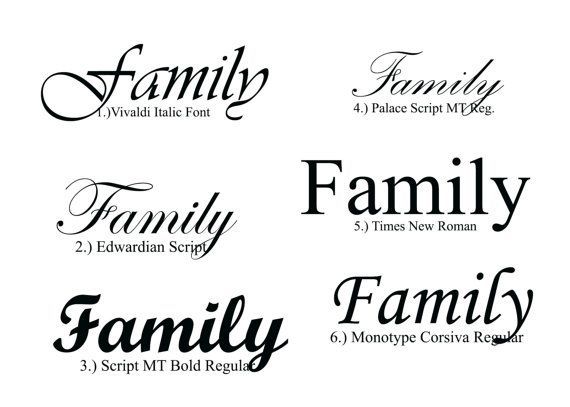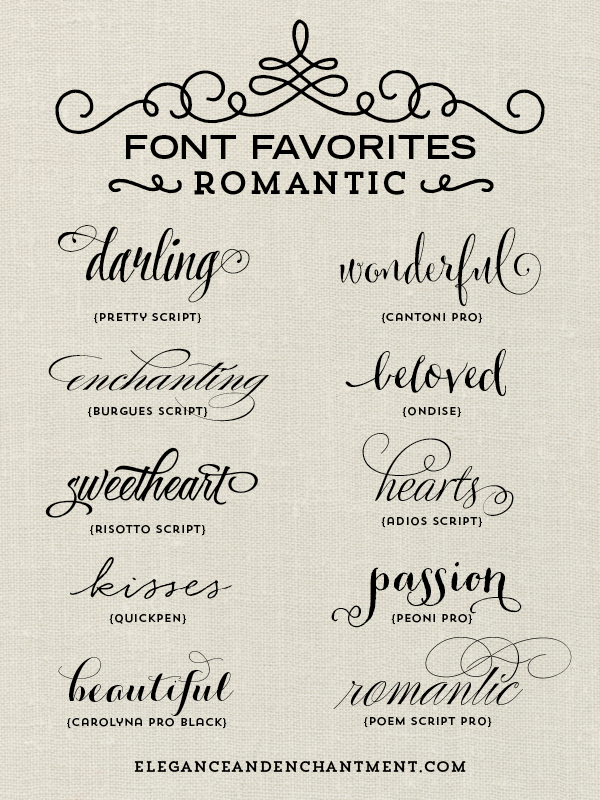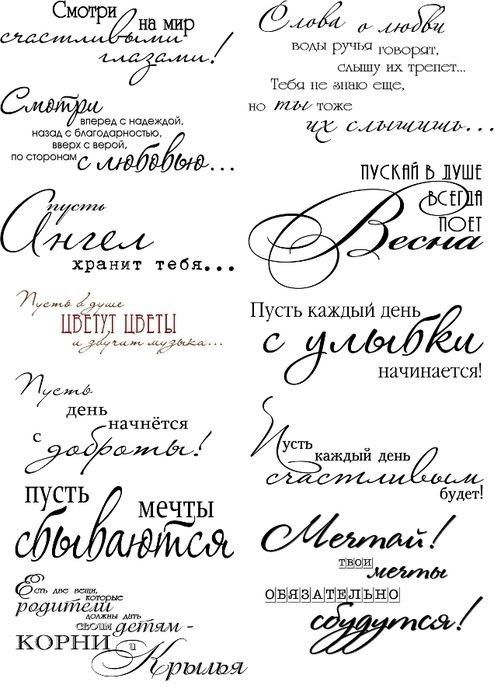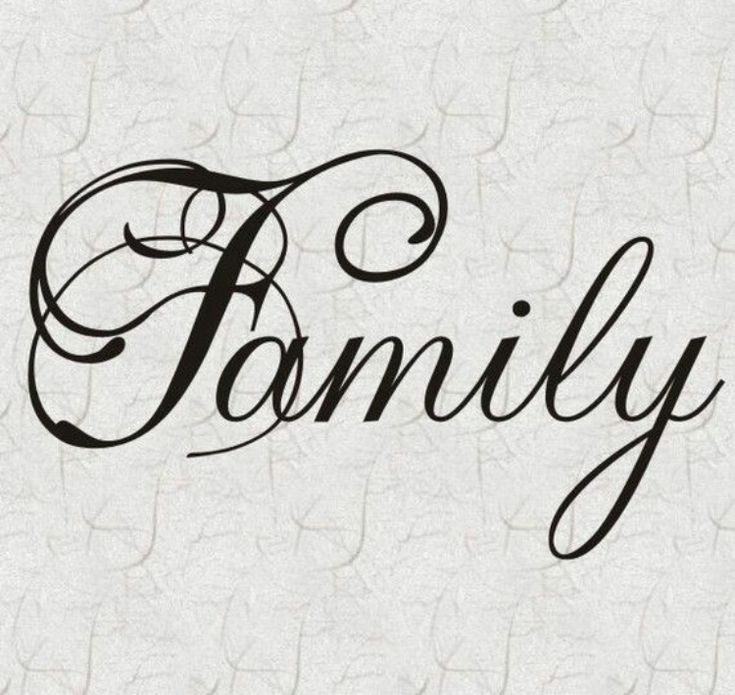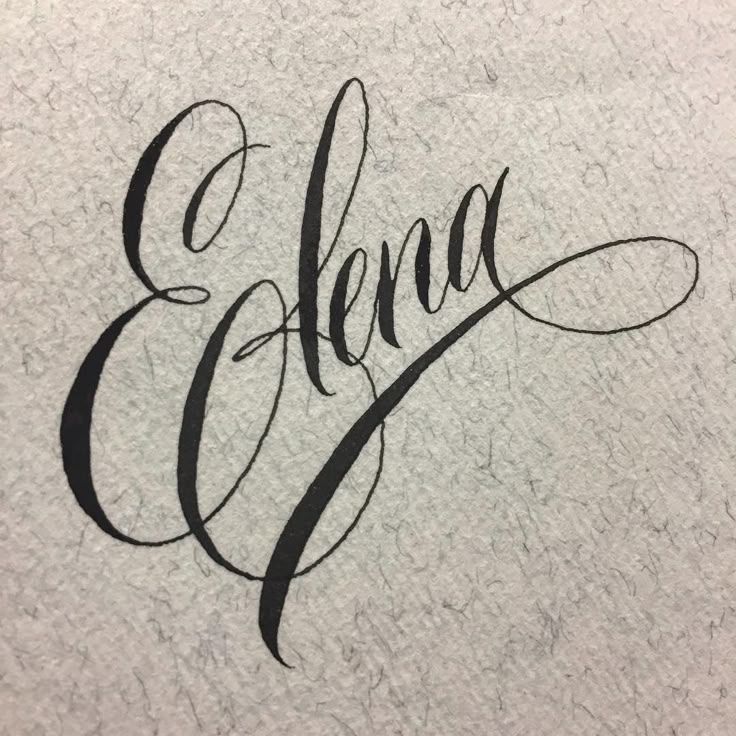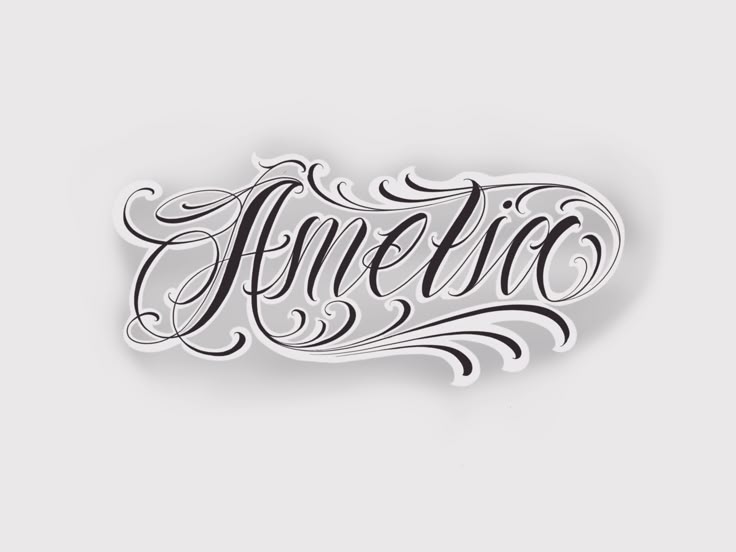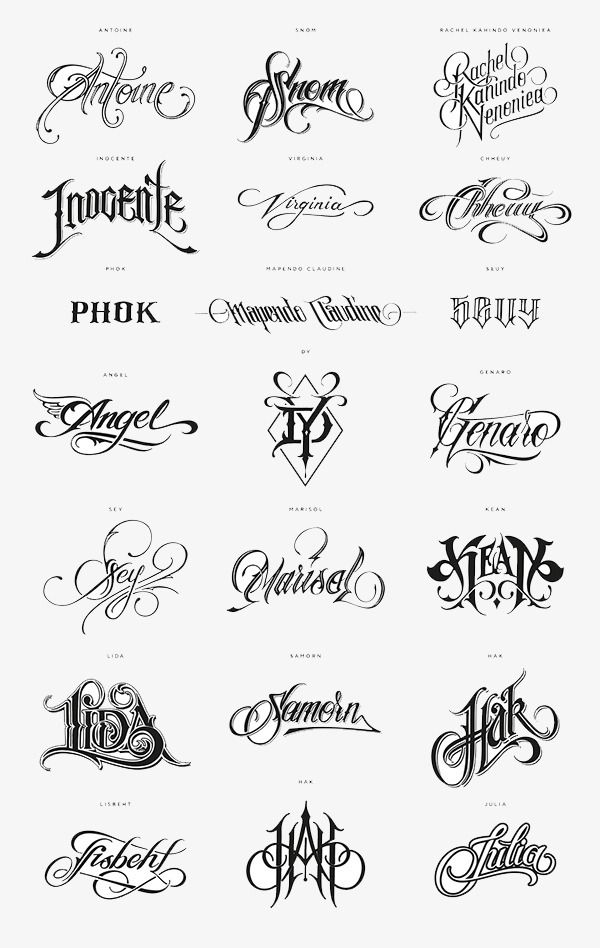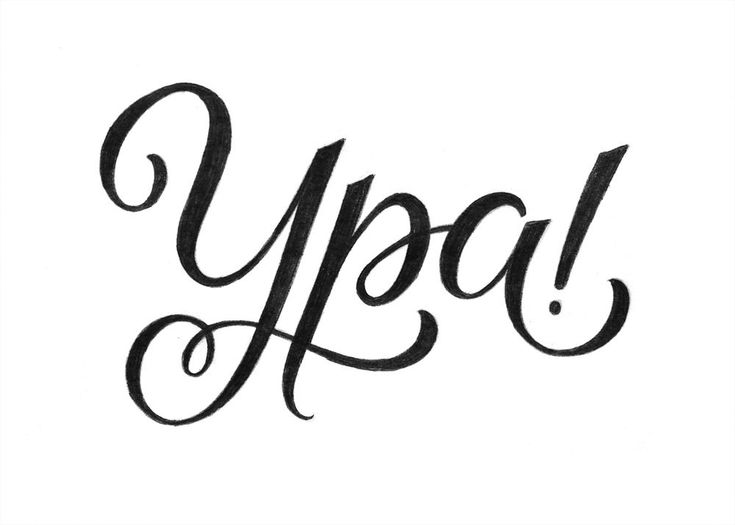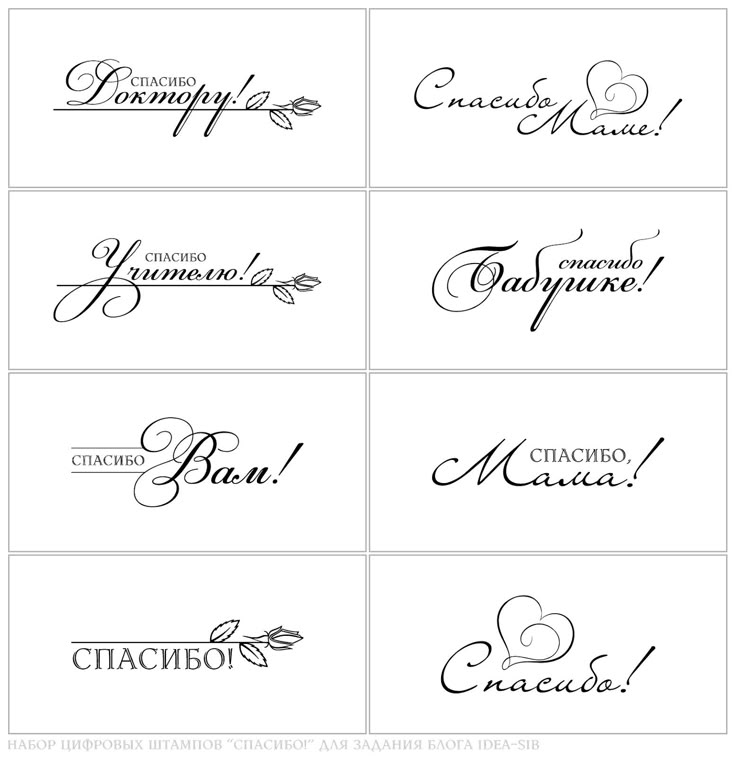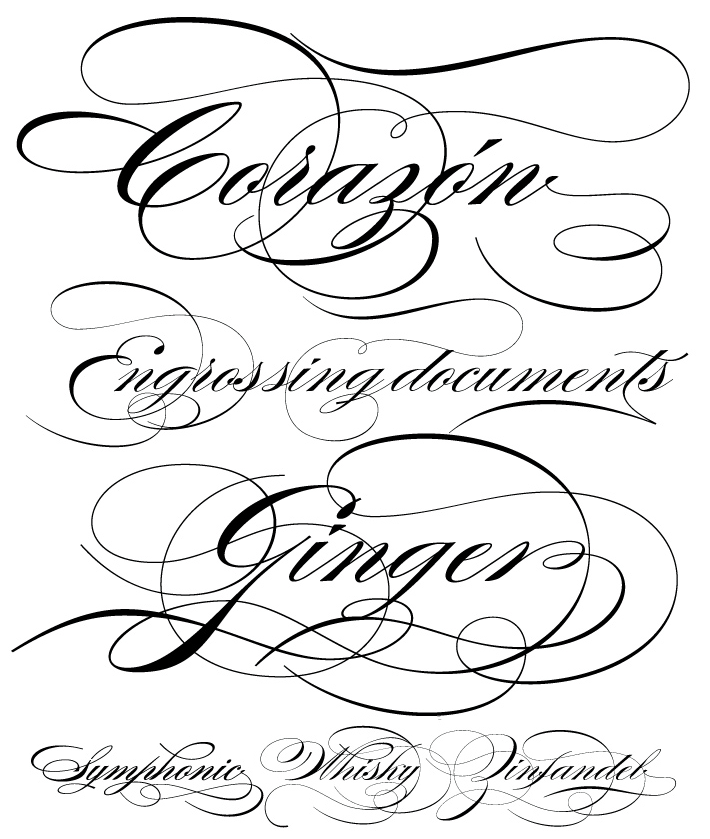
Красивый шрифт для поздравления — 71 фото
Какой шрифт лучше всего подходит для письма?
Существует множество причудливых шрифтов для надписей, поэтому вы можете легко выбрать тот, который соответствует вашему проекту. А еще есть много бесплатных шрифтов! Для подлинного рукописного стиля проверьте Himalaya Script , Luminaire или Amithen . Однако, независимо от того, хотите ли вы шрифт кисти или забавный шрифт с причудливым видом, у вас также гарантированно есть несколько хороших вариантов, например 9.